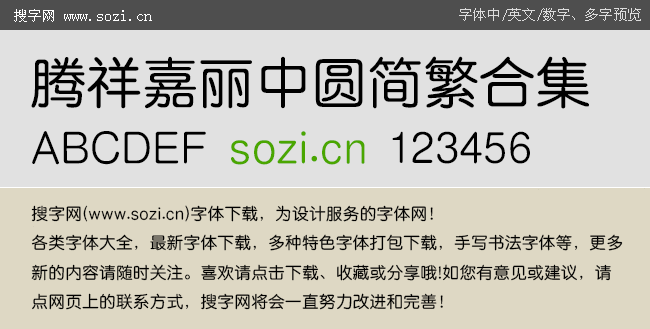
騰祥嘉麗中圓簡(jiǎn)繁合集
搜字網(wǎng)提供一款騰祥嘉麗中圓簡(jiǎn)繁合集中文藝術(shù)字體下載,騰祥嘉麗中圓是一款應(yīng)用于設(shè)計(jì)方面的簡(jiǎn)體中文漢字,該字體線條簡(jiǎn)潔圓潤(rùn),字形大方得體,整體效果出眾,并且字庫(kù)完整,可用于藝術(shù)設(shè)計(jì)、包裝印刷、簽名設(shè)計(jì)、圖形設(shè)計(jì)等領(lǐng)域。